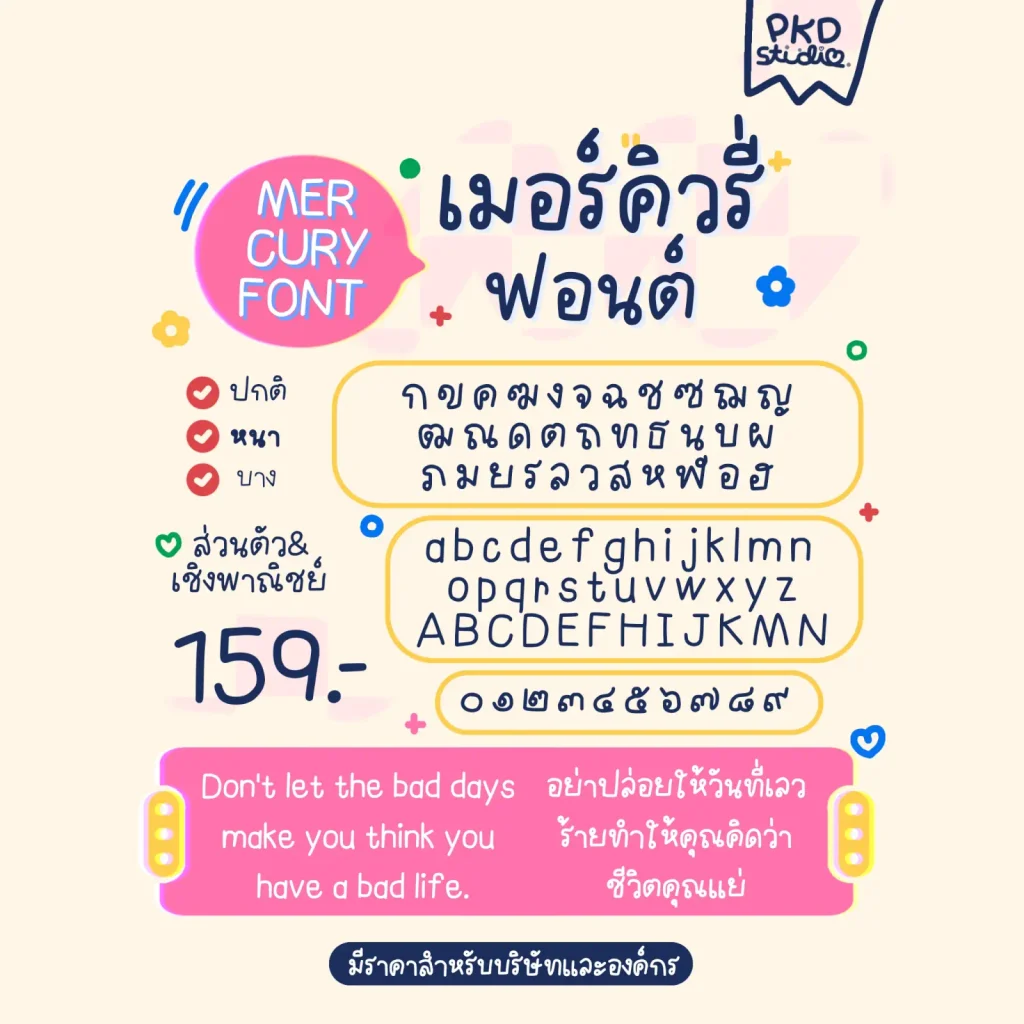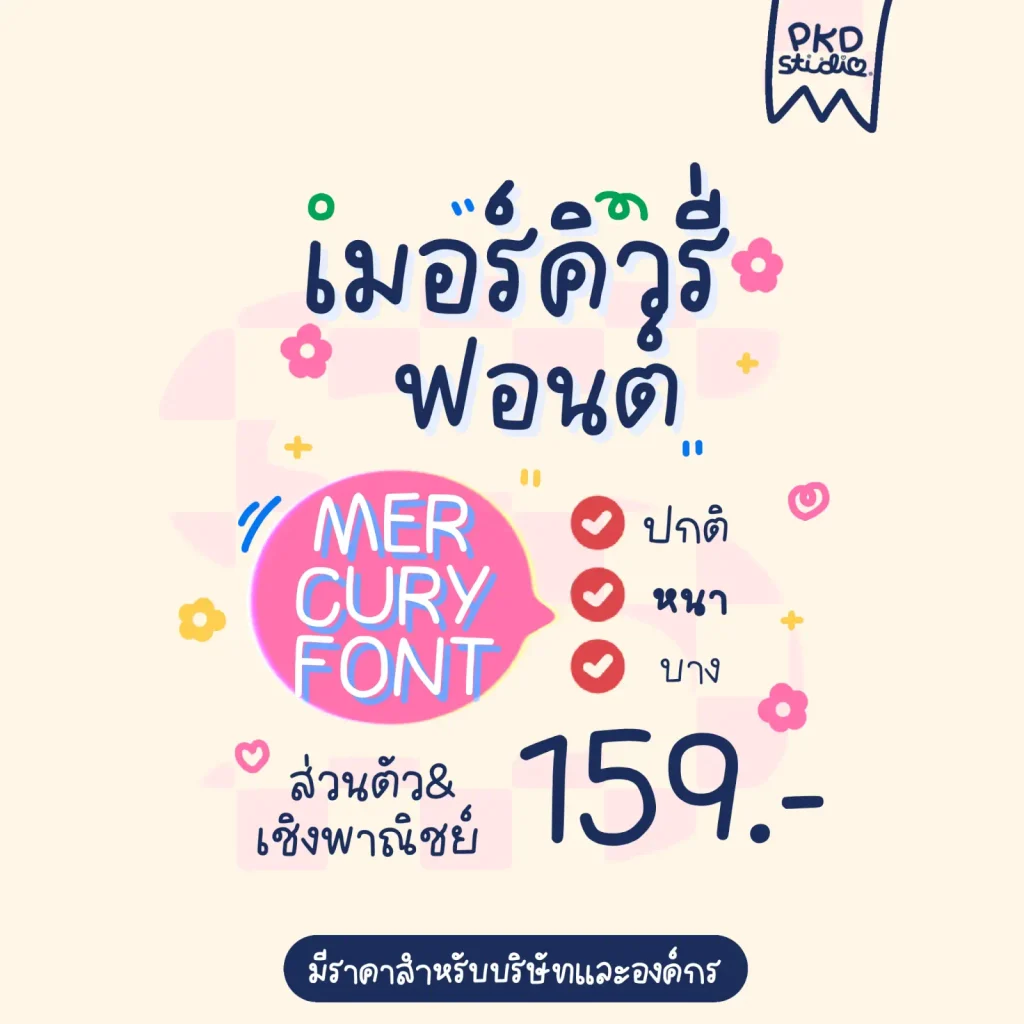
เมอร์คิวรี่ฟอนต์ (PKD Mercury) – ฟอนต์ลายมือน่ารัก สดใส เป็นกันเอง เหมาะสำหรับงานคอนเทนต์ โพสต์โซเชียล สติกเกอร์ คาเฟ่ และงานออกแบบทั่วไป
- ไม่มีตัวอักษรโปร่งผสม
- รองรับภาษาไทย ภาษาอังกฤษ ตัวเลข และสัญลักษณ์
เมอร์คิวรี่ (PKD Mercury)